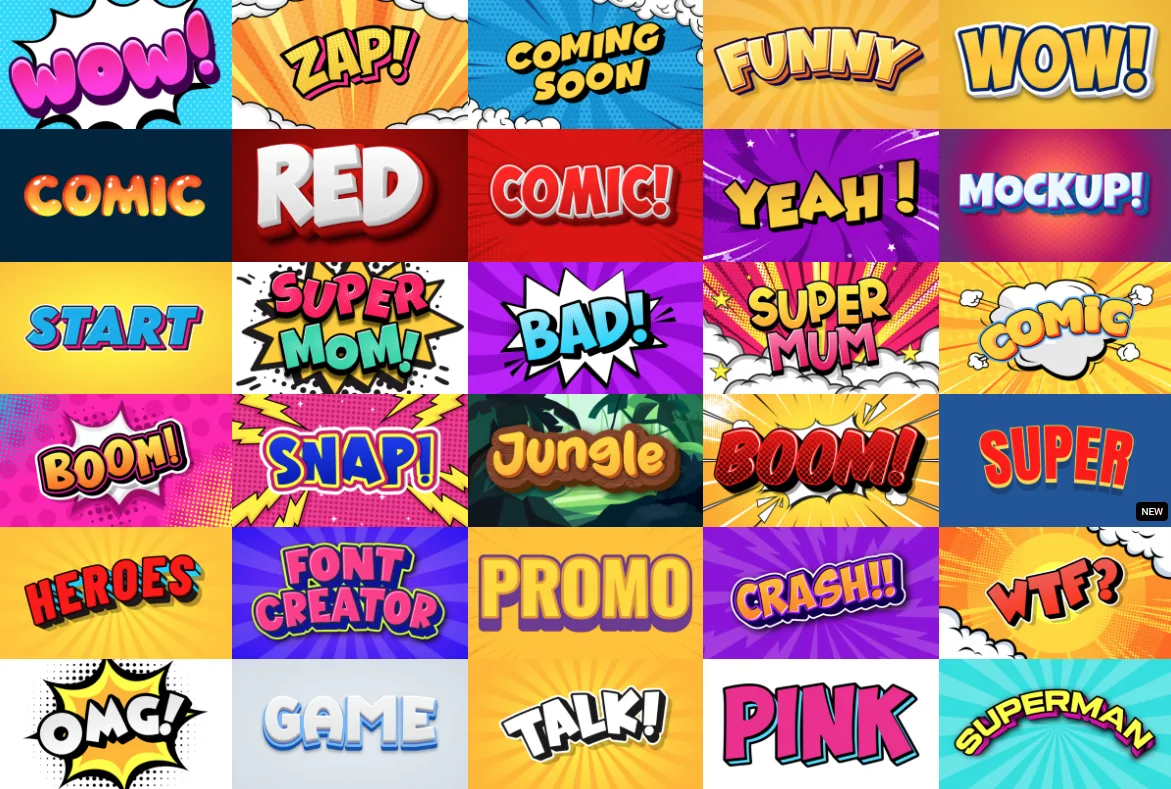
Комиксовые шрифты мгновенно вызывают улыбку. Они яркие, смелые и полны характера — идеально подходят для того, чтобы добавить дизайну игривости. Хотите ли вы создать заголовок в стиле супергероев, забавный мем или красочный логотип — комиксовый шрифт заставит ваше сообщение буквально выпрыгнуть с экрана. Давайте разберёмся, как использовать комиксовые текстовые эффекты, чтобы оживить ваши слова.
Почему комиксовые шрифты так популярны
Люди любят комиксовые шрифты за их выразительность и лёгкость восприятия. Толстые контуры и яркие цвета создают дружелюбное, мультяшное настроение, которое отлично смотрится на постерах, в видео и даже в детских проектах. Хороший комиксовый шрифт передаёт ту самую энергию рисунка от руки, которую можно встретить в классических комиксах или анимационных заставках.
Смелые и динамичные комиксовые текстовые эффекты
Комиксовый текстовый эффект добавляет движение, тень и выразительность — совсем как в ваших любимых панелях комиксов. Попробуйте сочетать чёткие контуры, полутоновые точки и красочные градиенты, чтобы создать этот броский стиль. Слова вроде «BOOM!», «WOW!» или «ZAP!» смотрятся потрясающе на фоне вспышки или расходящихся лучей. Это идеальный способ сделать текст живым и полным действия.
Стили шрифтов в духе супергероев и мультфильмов
Ищете что-то героическое? Супергеройский шрифт или мультяшный шрифт придаёт вашему сообщению выраженную 3D-глубину и уверенность. Используйте его для игровых логотипов, комиксов или постеров, которым нужен яркий характер. Красный, жёлтый и синий — классические цвета, которые сохраняют дизайн весёлым и энергичным.
Современное применение комиксовой типографики
Комиксовая типографика — это не только для детей. Дизайнеры используют комиксовые стили, чтобы добавить характер современному брендингу, превью для YouTube и дизайнам в стиле поп-культуры. В сочетании с 3D-тенями или глянцевыми бликами она создаёт классное сочетание ностальгии и современного творчества. Такой стиль ощущается спонтанным и динамичным — идеально, чтобы привлечь внимание в интернете.
Заключение